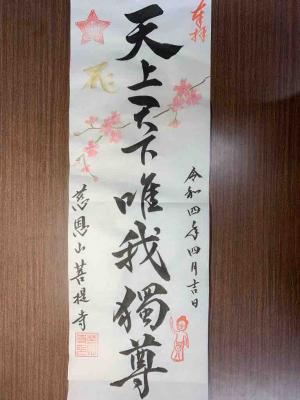
菓子亀さんのお饅頭は、どれをいただいても美味しい💕
白いちごだったので、お皿を別の色にすれば良かったぁ😨白い皿に、白いちご、白大福…💦別の色だったらもっと映えたんでしょうね💦
😞
4月、5月の御朱印対応日
4月、5月の御朱印対応日です😊
4月はいつも通り土曜日、5月は14日がお休みとなりますので、お間違えないようお願い致します🙇‍♀️
5月1日はマジパレまつりで、5月14日は、美濃路稲葉宿にて書道パフォーマンスをします。
5月14日は、稲沢市観光協会よりお声がかかり、書道パフォーマンスすることになりました❗️
是非、遊びにいらして下さい🙇‍♀️
今年もマジパレまつりで書道パフォーマンスします😊
今年もマジパレまつりが開催されます😊
マジカルパレードビーチさん、SEAMOさんもライブを❗️
楽しみですね~😊
私も書道パフォーマンスをさせていただきますので、遊びにいらして下さい🙇‍♀️😊
お礼の絵はがき
お供えとかお心遣いを下さった方に、お礼の絵はがきを送らせていております😊
最近はチュウリップに蝶の絵はがきです❗️
最近いただいたお供え、お心遣い、お土産です😊
皆様、ありがとうございました🙇‍♀️💕
通年御朱印 夢叶う象
象さん😊
鼻から花😆
夢叶うという花言葉の青薔薇❗️薔薇が十本で、あなたは全てが完璧ですという意味。なので、完璧だから夢叶うということ😊
夢叶うぞう😆
通年で書かせていただきます❗️
天上天下唯我独尊
お釈迦様が誕生された時に発したお言葉😊
「天上天下唯我独尊」
4月8日が生誕日、灌仏会、花まつりとして、お釈迦様に甘茶をかけたりしますね!
4月限定の御朱印です😊
蝶と春薔薇をハーフサイズにも
蝶と春薔薇、ハーフサイズにも😊
蝶と春薔薇、白にも黒にもハーフサイズにも人気です😊
ぱふぇちゃんの近況😊
ぱふぇちゃんの近況です😊
気持ちよさそうにすやすや💤
可愛い💕
お礼の栞 チュウリップと薔薇
お礼の栞です😊
春らしく、チュウリップと蝶🦋
菩提寺の駐車場の隣に、輝々ハウスの方々が植えて下さったチュウリップの球根、まだ花は咲いてませんが、そろそろですね~😊
楽しみ😊
春爛漫を黒の御朱印帳に
春爛漫を黒の御朱印帳にお書き入れ😊
キラキラと映えますね~✨
ワクチンの副反応、昨日はなんともなく、スッキリでした😊
お気遣いをいただき、ありがとうございました🙇‍♀️
今日は幼稚園の卒園式です㊗️
2年間一緒にお稽古したみんなとさよならするのは、寂しいものです💦
春詣を黒の御朱印帳に
春詣を黒の御朱印帳にお書き入れすると😊
黒も可愛い💕
3回目のワクチンの副反応ですが、昨日の朝は接種した腕が少し痛い程度でしたが、だんだんと痛くなり💦倦怠感と微熱も出てきましたので11時にゴロンと横になり、13時までゆっくりして、カロナールを飲んだら、少し楽になり、また御朱印のお書き入れ_φ(・_・
母に、無理しないようにと言われましたが、無理をしてしまう私でした😆
蝶と春薔薇を黒の御朱印帳に
蝶と春薔薇を黒の御朱印帳にもお書き入れさせていただいております😊
黒の御朱印帳にも素敵になりますね~✨
昨日の夕方、3回目のワクチンを接種しました。モデルナというお話でしたが、ファイザーでした😊
今のところ、副反応はありませんが…、今日は授業もお稽古もないので、無理のないよう、御朱印のお書き入れをします😊
蝶と春薔薇を金の御朱印帳に
蝶と春薔薇を金の御朱印帳にお書き入れすると😊
金にお書き入れすると豪華な感じになりますね~✨ただ、金の御朱印帳に関しましては、ご参拝の方の御朱印帳を見てからの受付となりますので、ご了承下さい🙇‍♀️
お花印帳へのお書き入れ
お花印帳へお書き入れ😊
春バージョンです😊
あとはお花屋さんが可愛く仕上げて下さいます💕楽しみですね😊